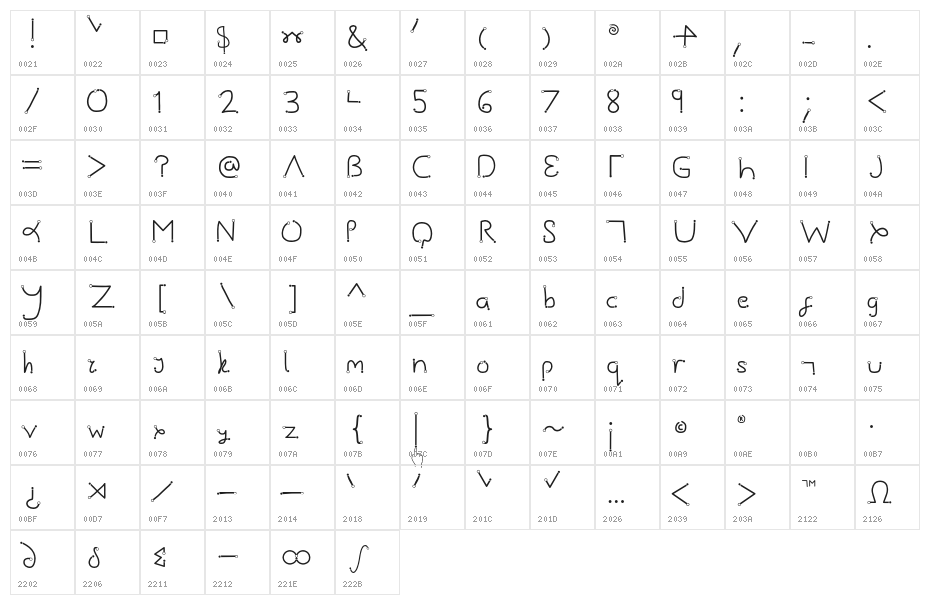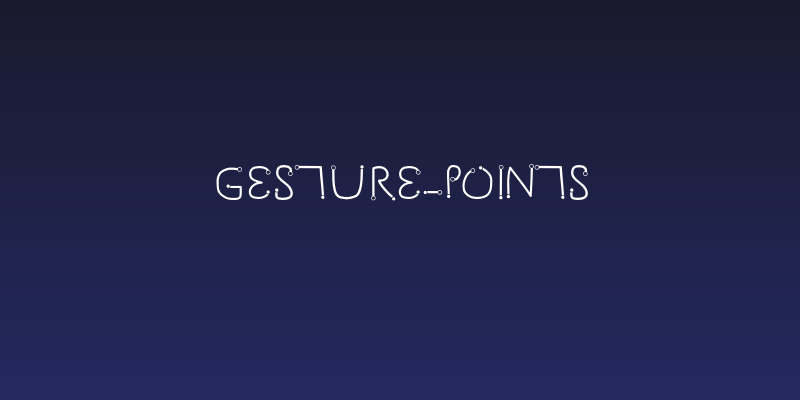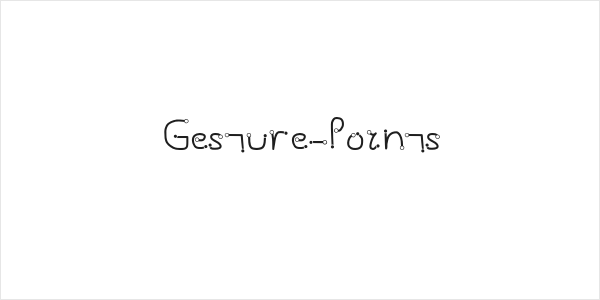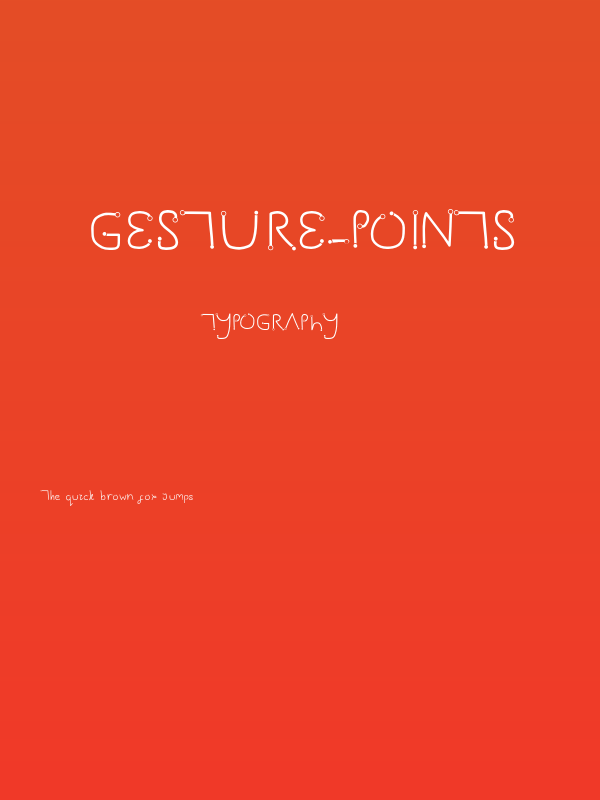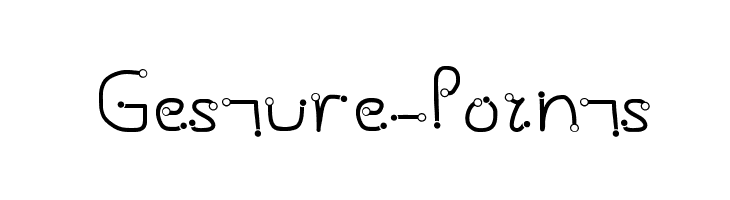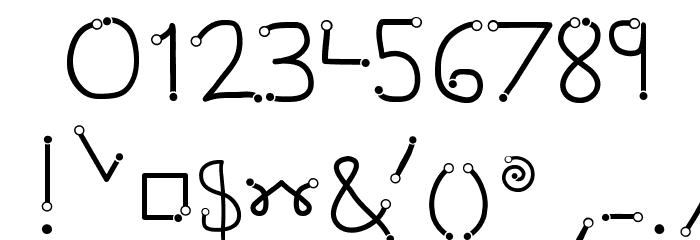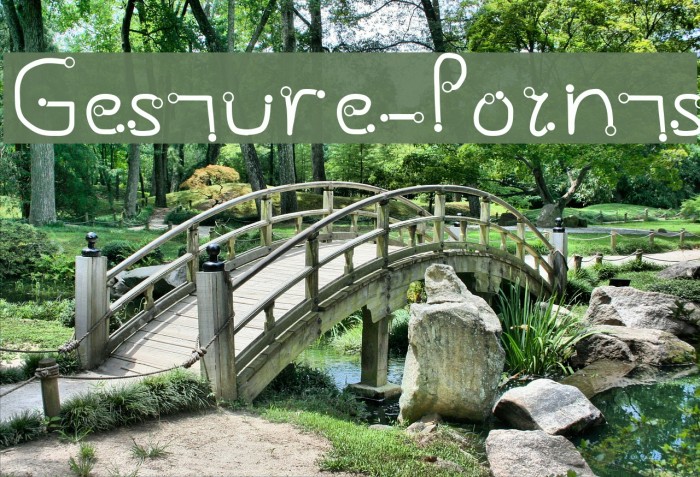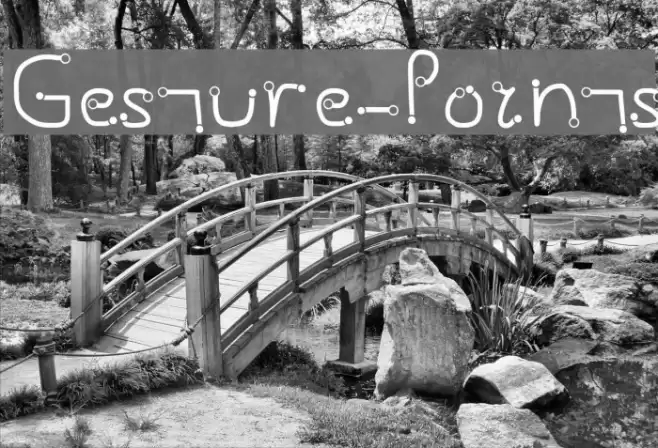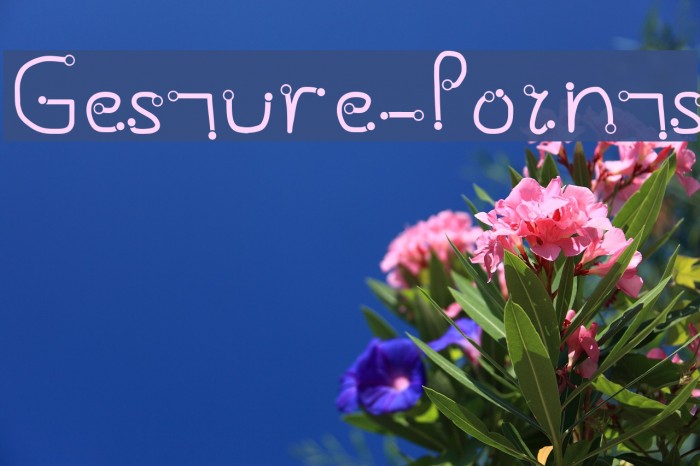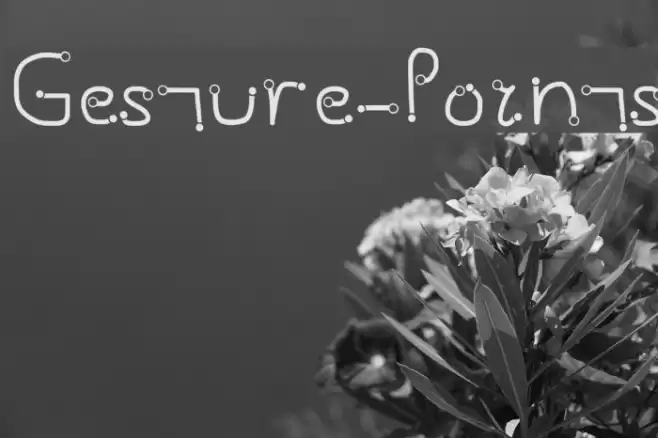
Gesture-Points Font
GESTURE-POINTS Groß
GESTURE-POINTS Kleinbuchstaben
GESTURE-POINTS Anderer Schreiben
| Name | Gesture-Points |
| Gewicht | Points |
| Gesamtstil | Modern, Decorative |
| Anwendungsfall | Headlines, Logos, Creative projects |
| Vorgeschlagene Projekte | Ideal for children's books, playful branding, creative posters, and artistic invitations. |